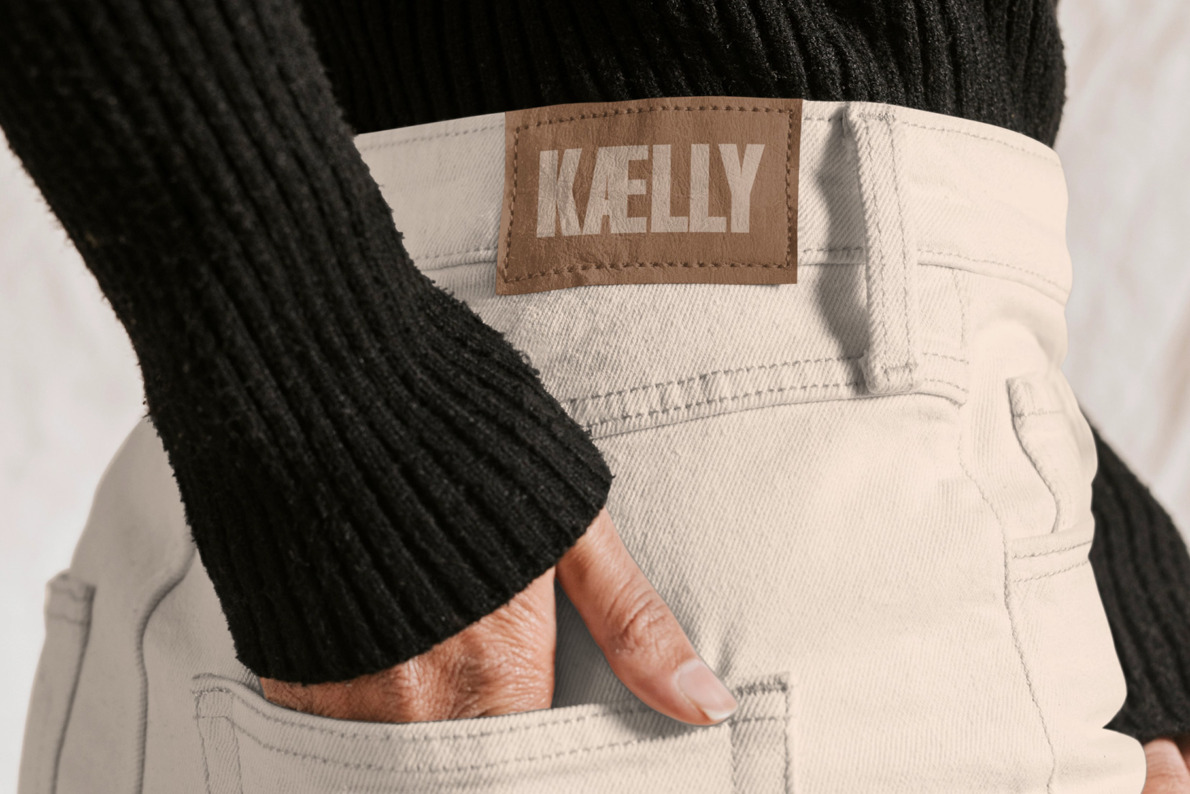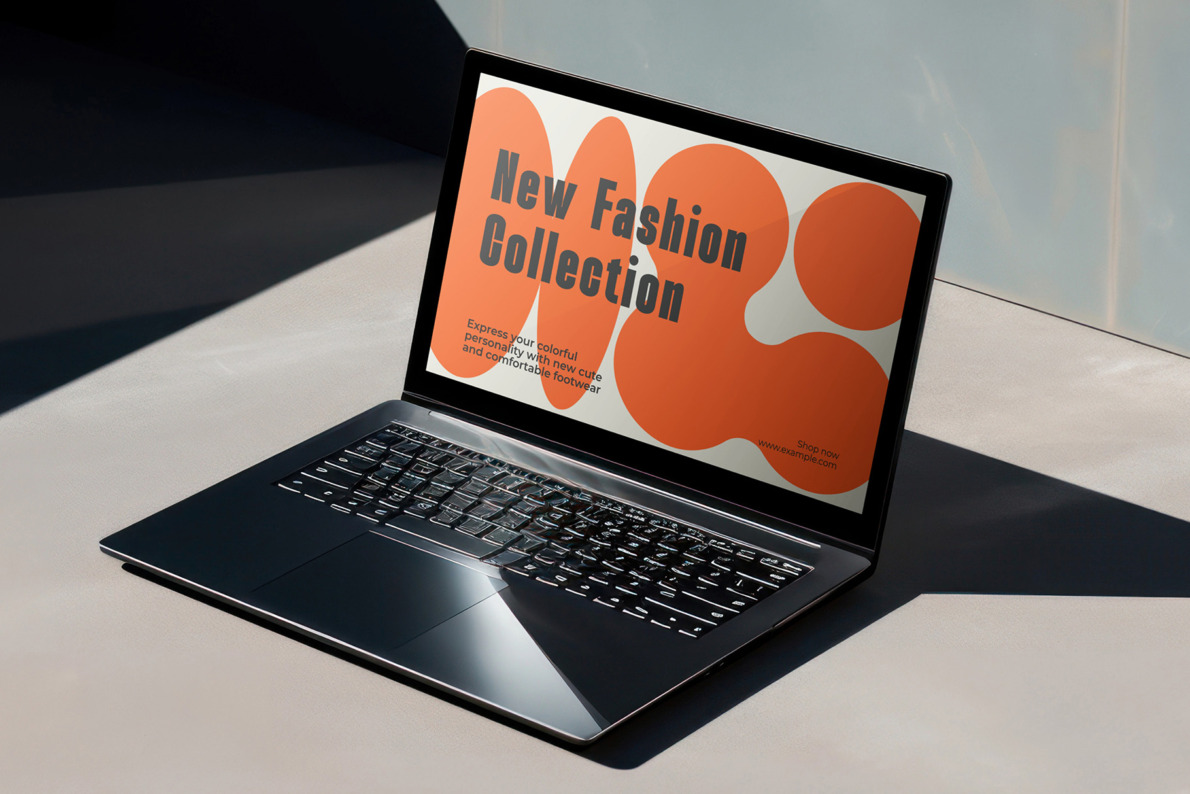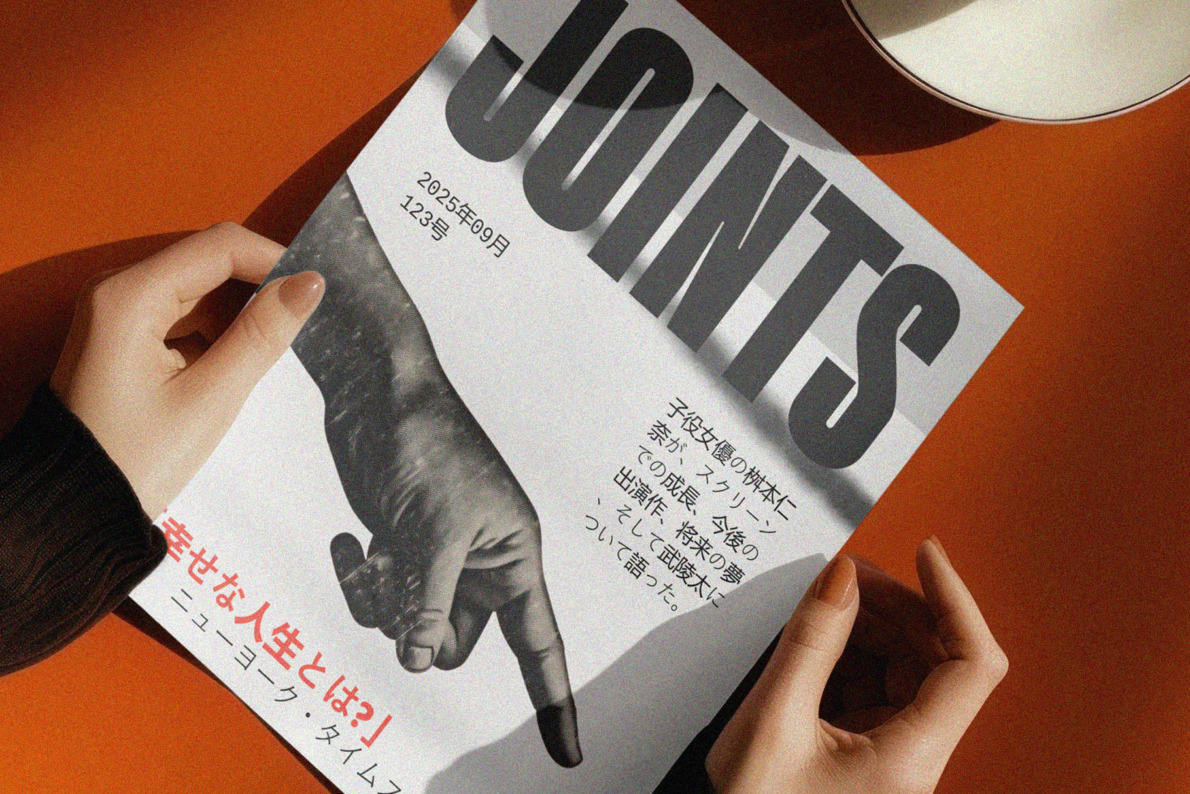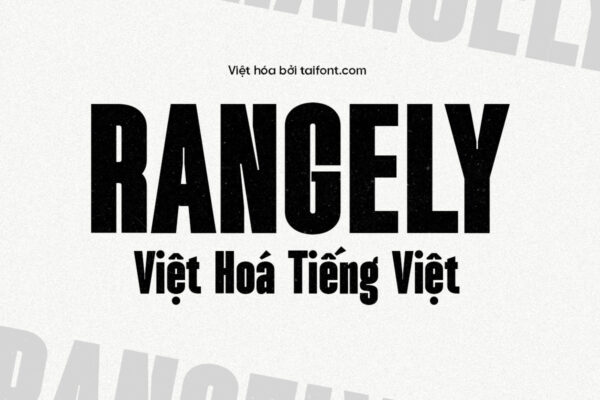
Giới thiệu về Font TF Rangely Việt hóa
TF Rangely Việt hóa là một font chữ không chân (sans-serif) nổi bật với thiết kế đẹp mắt, dáng cao và nét đậm, mang đến vẻ ngoài hiện đại, mạnh mẽ và đầy ấn tượng. Font này toát lên phong thái chuyên nghiệp, rõ ràng và có sự hiện diện nổi bật, lý tưởng để thu hút mọi ánh nhìn và truyền tải thông điệp một cách trực tiếp.
Với đặc điểm là kích thước lớn, độ dày ấn tượng và tính thẩm mỹ cao, Rangely là lựa chọn lý tưởng cho các thiết kế muốn truyền tải sự mạnh mẽ, uy tín và phong cách:
- Thiết kế thời trang: Hoàn hảo cho các thương hiệu thời trang, từ logo, nhãn mác sản phẩm, lookbook, đến các chiến dịch quảng bá bộ sưu tập. Font này giúp truyền tải vẻ đẹp hiện đại, mạnh mẽ và độc đáo của trang phục, nâng tầm giá trị thương hiệu.
- Tiêu đề: Lý tưởng để tạo các tiêu đề chính trên poster, banner, hoặc các ấn phẩm truyền thông cần sự chú ý tối đa. Dáng cao và nét đậm của font giúp thông điệp của bạn “nhảy” ra khỏi trang, dễ dàng gây ấn tượng sâu sắc.
- In ấn: Đảm bảo khả năng đọc tốt ngay cả ở kích thước lớn, và tạo hiệu ứng thị giác mạnh mẽ khi in trên các chất liệu khác nhau như giấy, vải, hay biển hiệu.
- Tạp chí: Phù hợp để sử dụng cho các tiêu đề chính, lời dẫn hoặc các bài viết đặc biệt trong các tạp chí thời trang, nghệ thuật, hoặc tạp chí về phong cách sống. Nét đậm và rõ ràng của Rangely sẽ làm cho nội dung nổi bật và thu hút độc giả.
Với TF Rangely Việt hóa, bạn có thể dễ dàng thổi hồn mạnh mẽ, năng lượng và sự độc đáo vào các thiết kế, tạo ra những sản phẩm không chỉ đẹp mắt mà còn cực kỳ ấn tượng và có khả năng thu hút sự chú ý tối đa.
Font Việt hóa TF Rangely – Phong chữ thời trang tạp chí